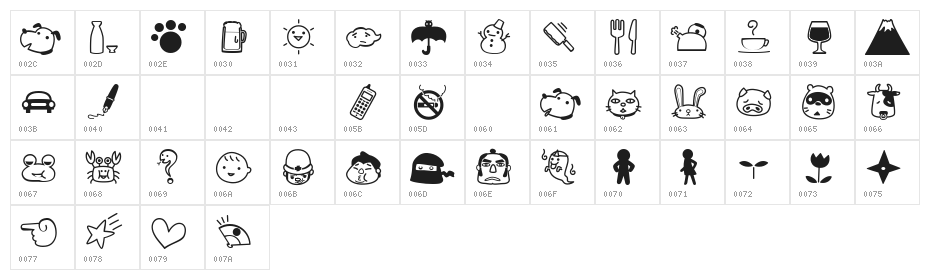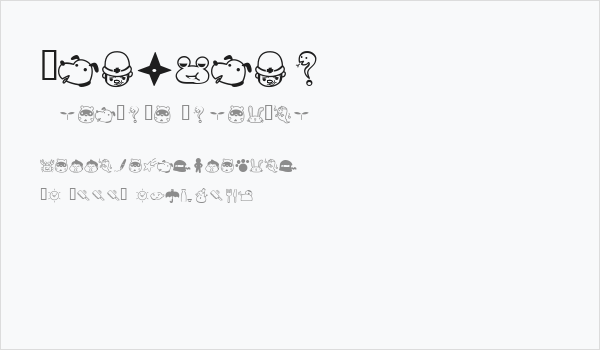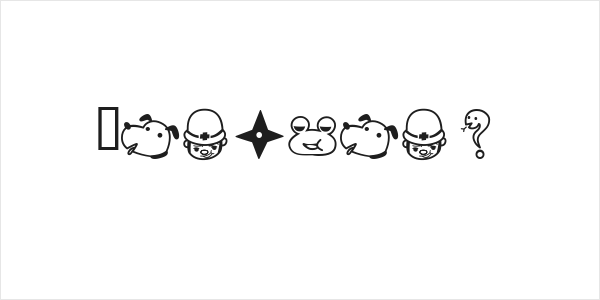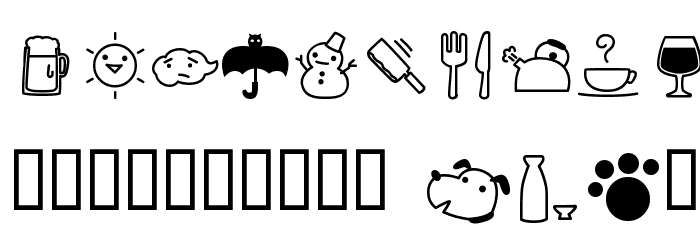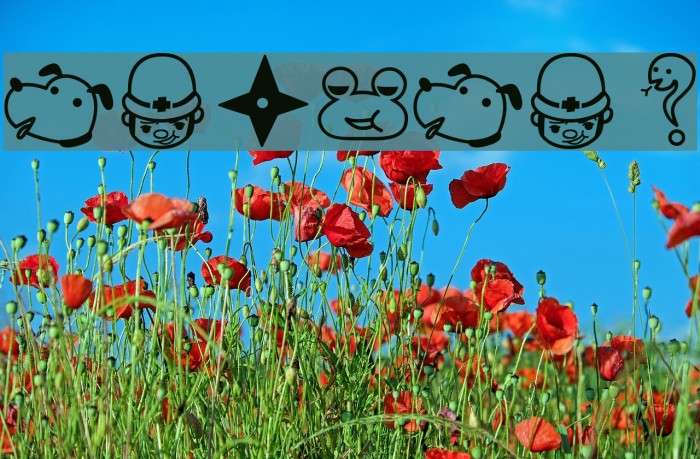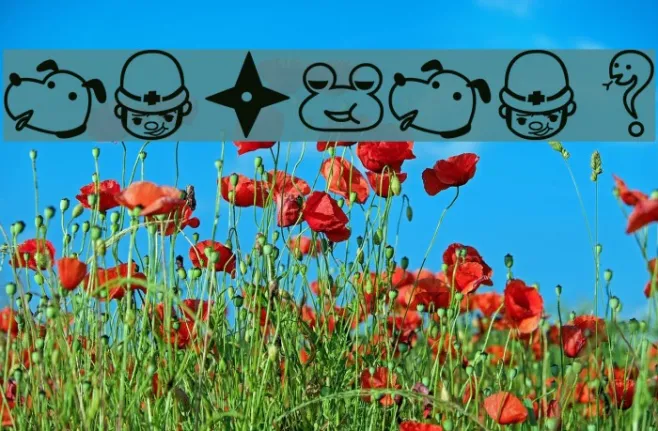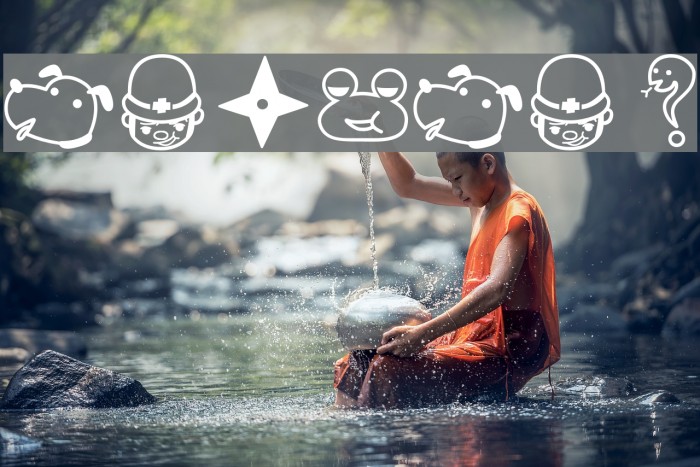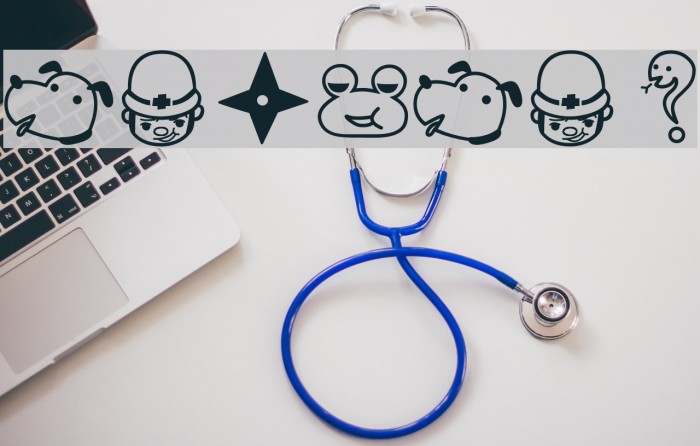
Rakugaki Font
✎ Dingbats
| Style général | Playful, Whimsical, Cartoonish |
| Cas d'utilisation | Decorative elements, Informal branding, Children's materials |
| Projets proposés | Ideal for children's books, playful branding, casual invitations, and creative digital content. |